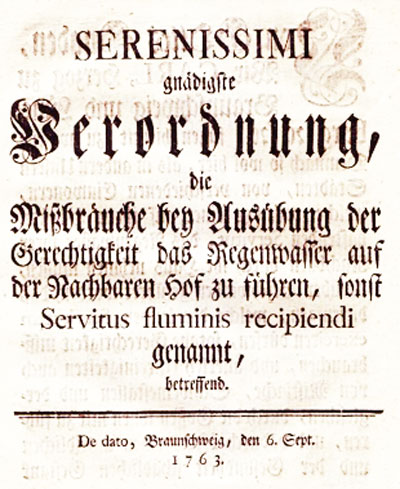
Fraktur und Antiqua gemischt - welche würden passen?
für eine auf retro bzw. auf die Jahre um 1918 getrimmte Werbung suche ich eine Fraktur, die man mit einer Antiqua kombinieren kann (allerdings keine Mischformen), sodass es immer noch schön aussieht. Der Gegensatz soll deutlich auffallen, allerdings nicht störend wirken - wie z.B. hier:
Vermute, dass das eine Geschmackssache ist und bin deshalb für jeden Ratschlag und jede Kombinationsmöglichkeit dankbar!
Um die Gestaltung möglichst authentisch wirken zu lassen, würde ich mir zunächst mal die aus der Zeit stammenden Schriften aus beiden Kategorien (Antiqua/Fraktur) zusammen suchen und dann schauen, was gut miteinander funktioniert.
Mit genau solchem Mischsatz habe ich vor ein paar Tagen mal experimentiert, und zwar unter Einsatz von Schriften aus der Fell-Type-Kollektion:
Kostenlos und für diesen Zweck m. E. recht brauchbar, besonders, wenn die verwendete Fraktur auch ein  wenig ruppiger ist. Für 1918 allerdings, wie auch das von Dir hochgeladene Beispiel, vielleicht etwas früh ;-)